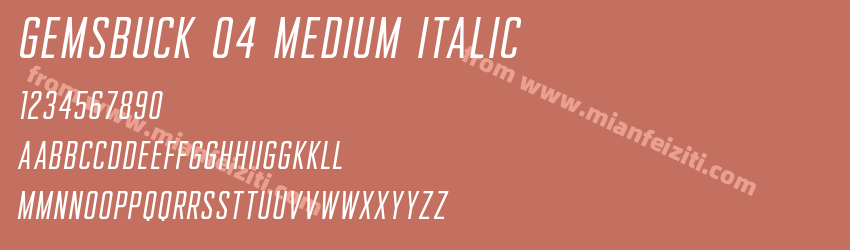
Gemsbuck 04 Medium Italic
字体名称: Gemsbuck 04 Medium Italic
Postscript名称: Gemsbuck04-Medium-Italic
字体字重: Medium-Italic
本款“Gemsbuck 04 Medium Italic”是一款书写很新颖的字体,字体大方,适合各种设计作品使用!欢迎下载!